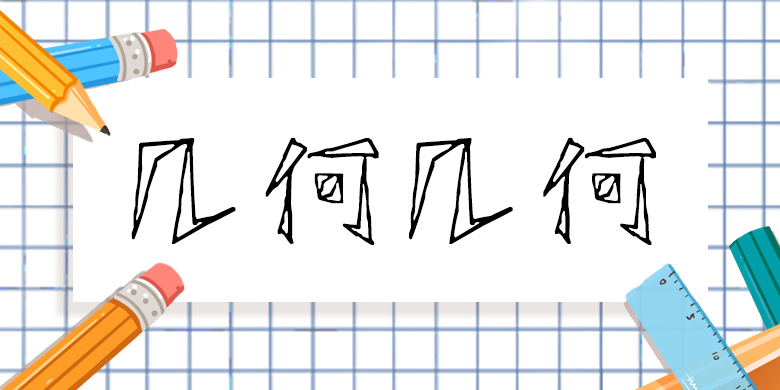
品牌:方正手迹设计师:赵倩发行时间:2017字库编码:大陆简体(GB2312-80)分类:创意书写字体属性:精品字
每个笔画采用空心的处理方式,独具特色的笔画造型,创造出极具特色的创意字体,好像七巧板巧妙拼出每个字。棱角分明又虚怀若谷,值得细细品味。 适用于少年儿童类的书刊、品牌广告和产品包装设计,以及社交网络的个性化用字。